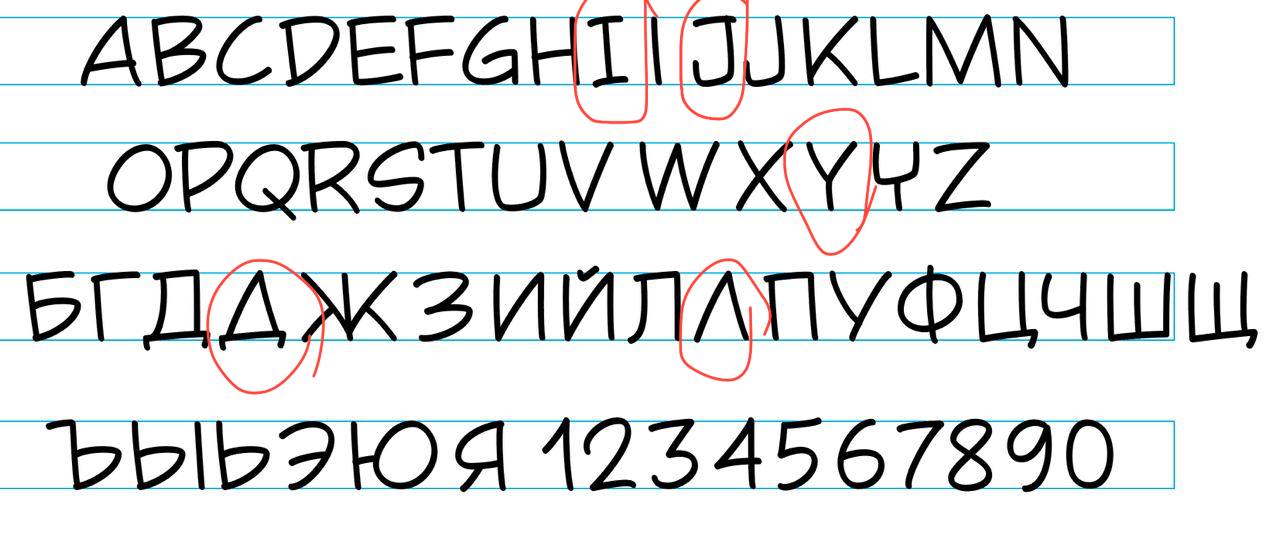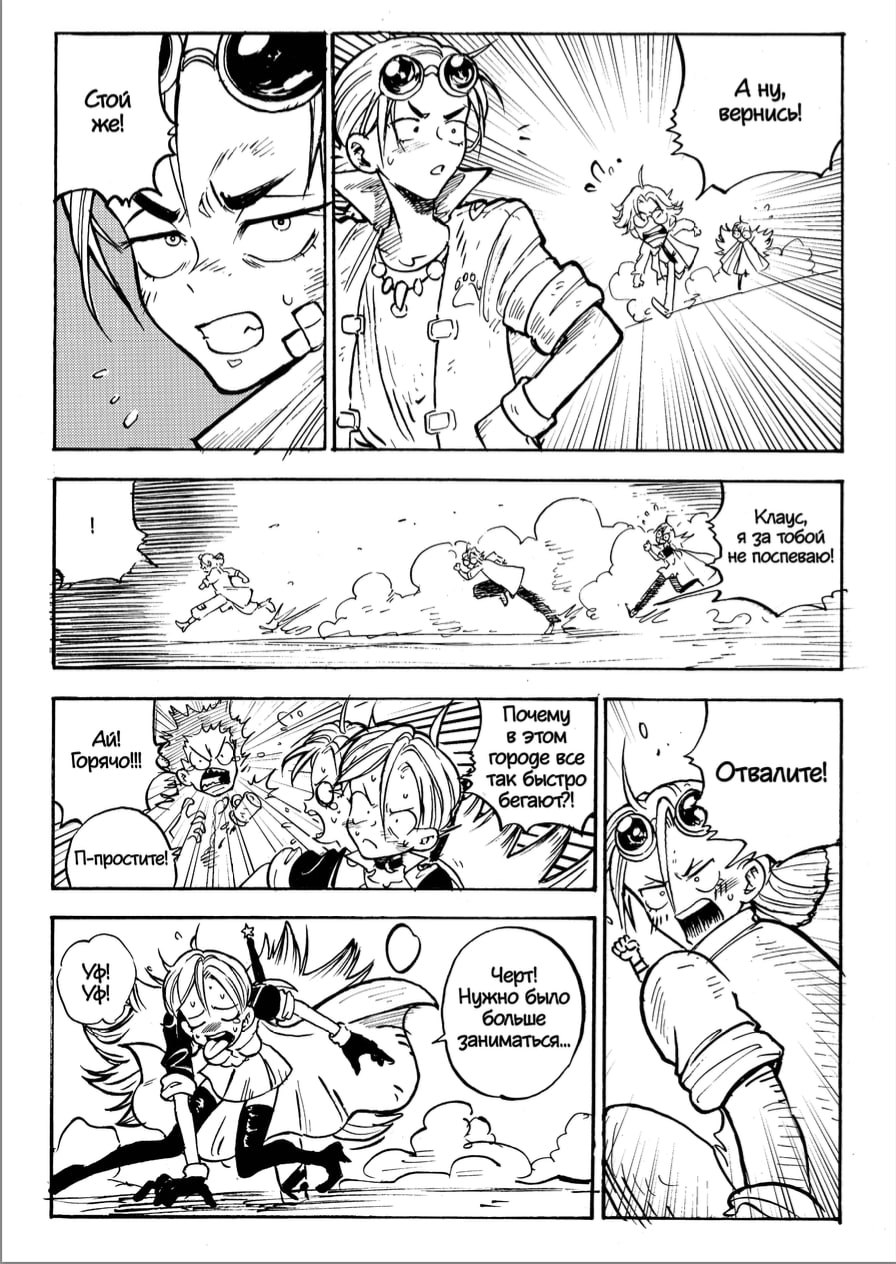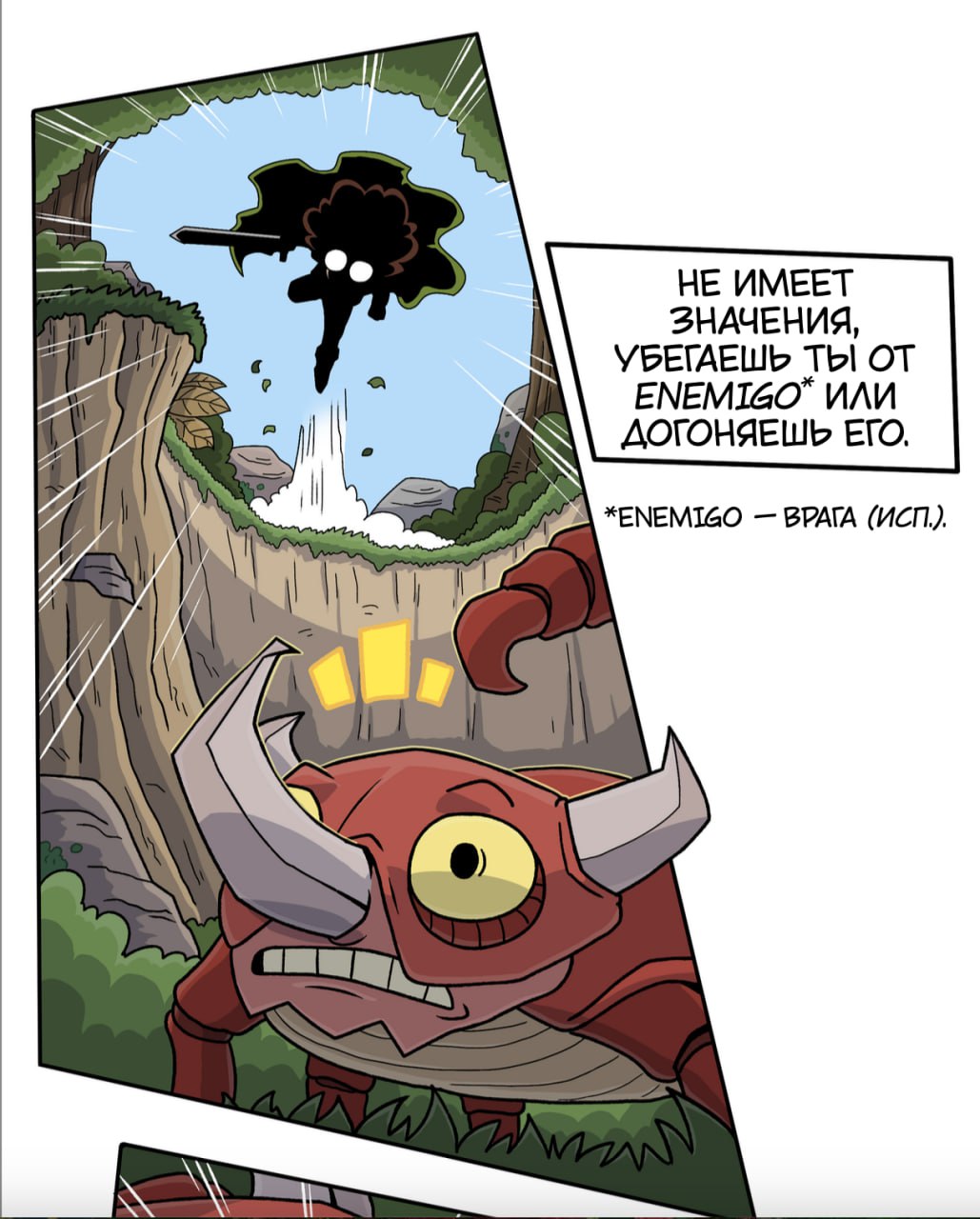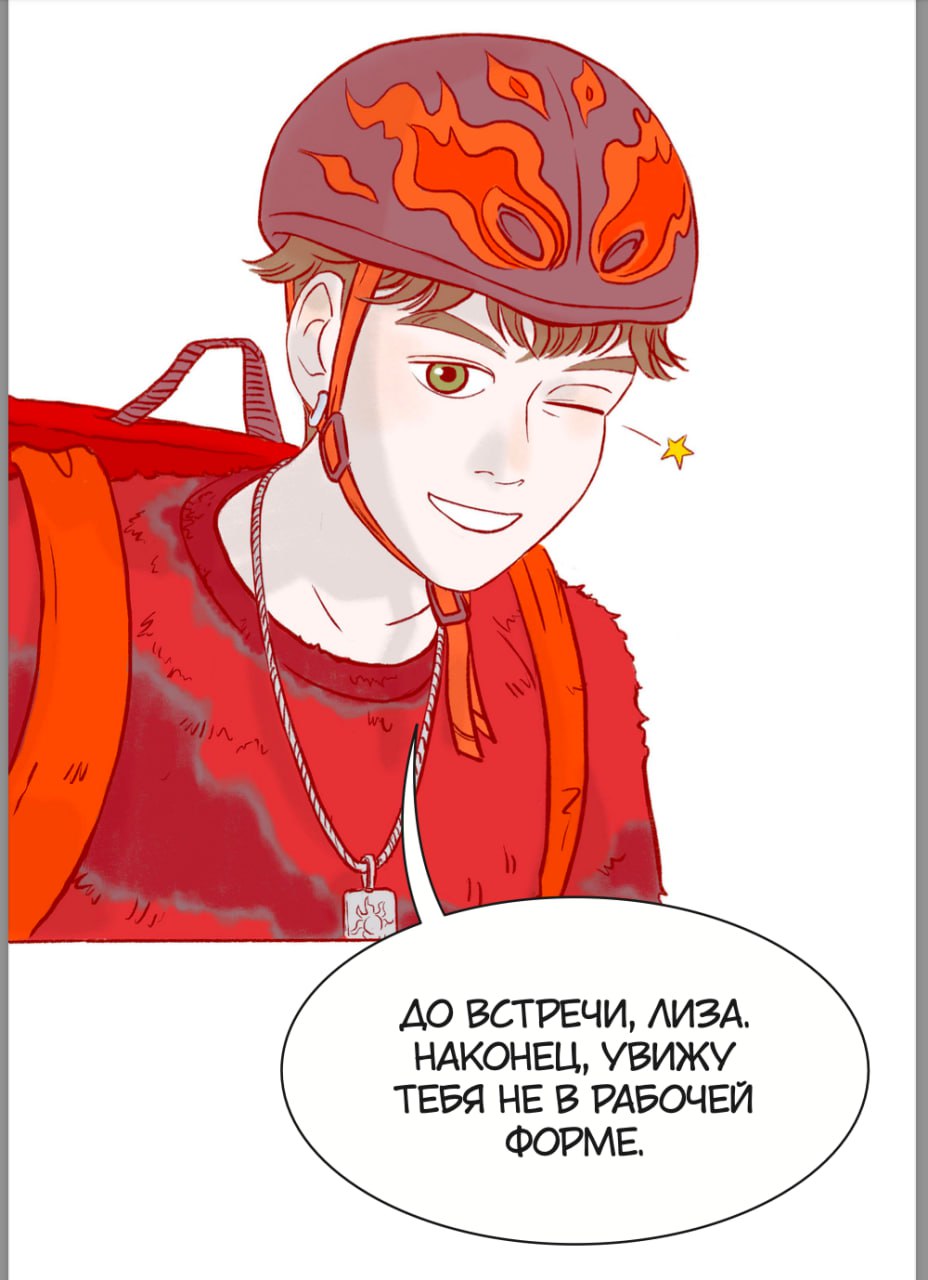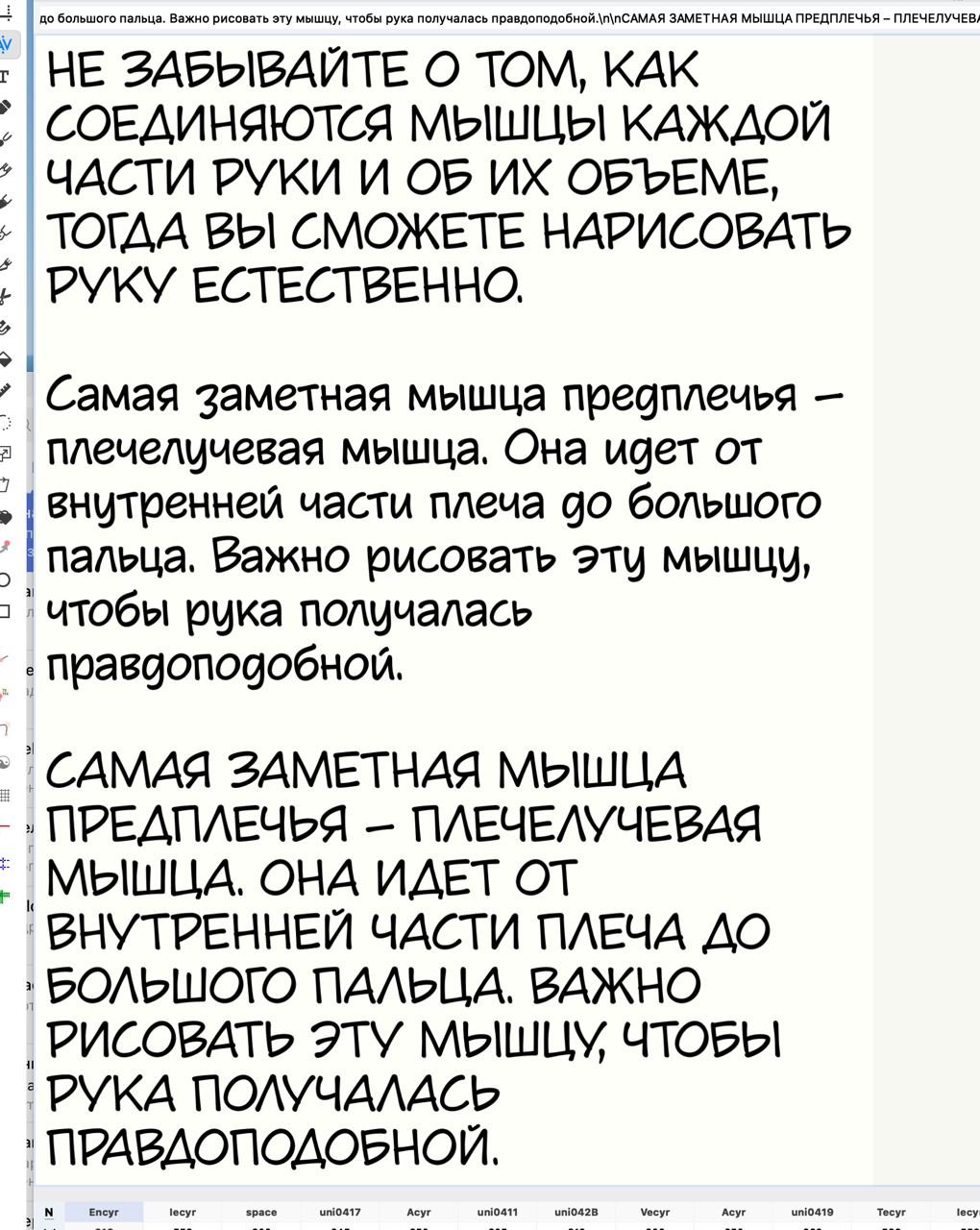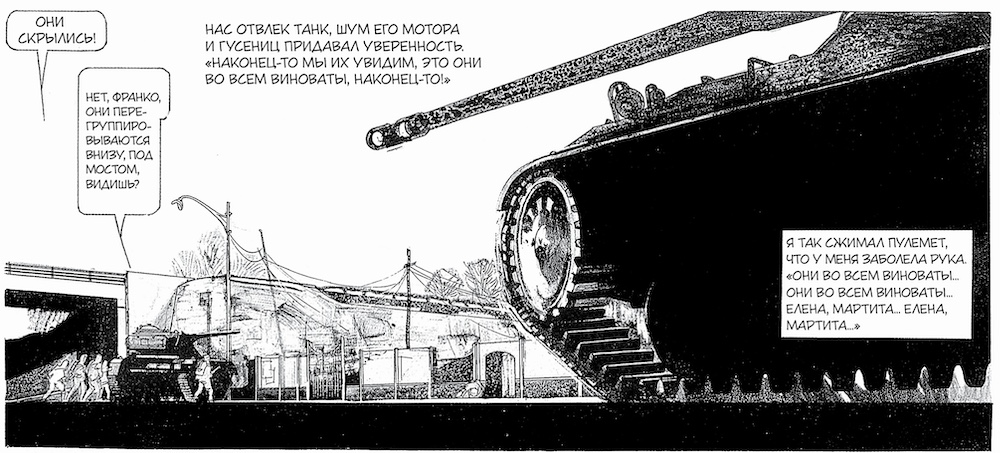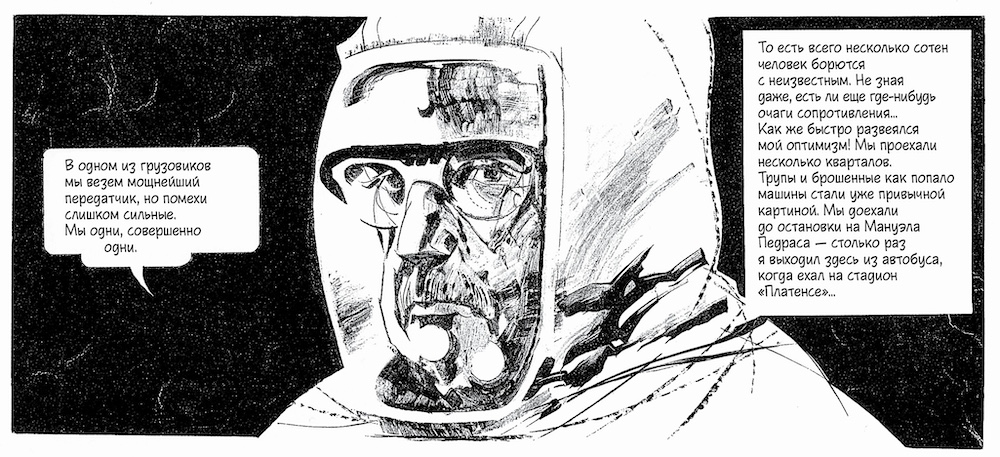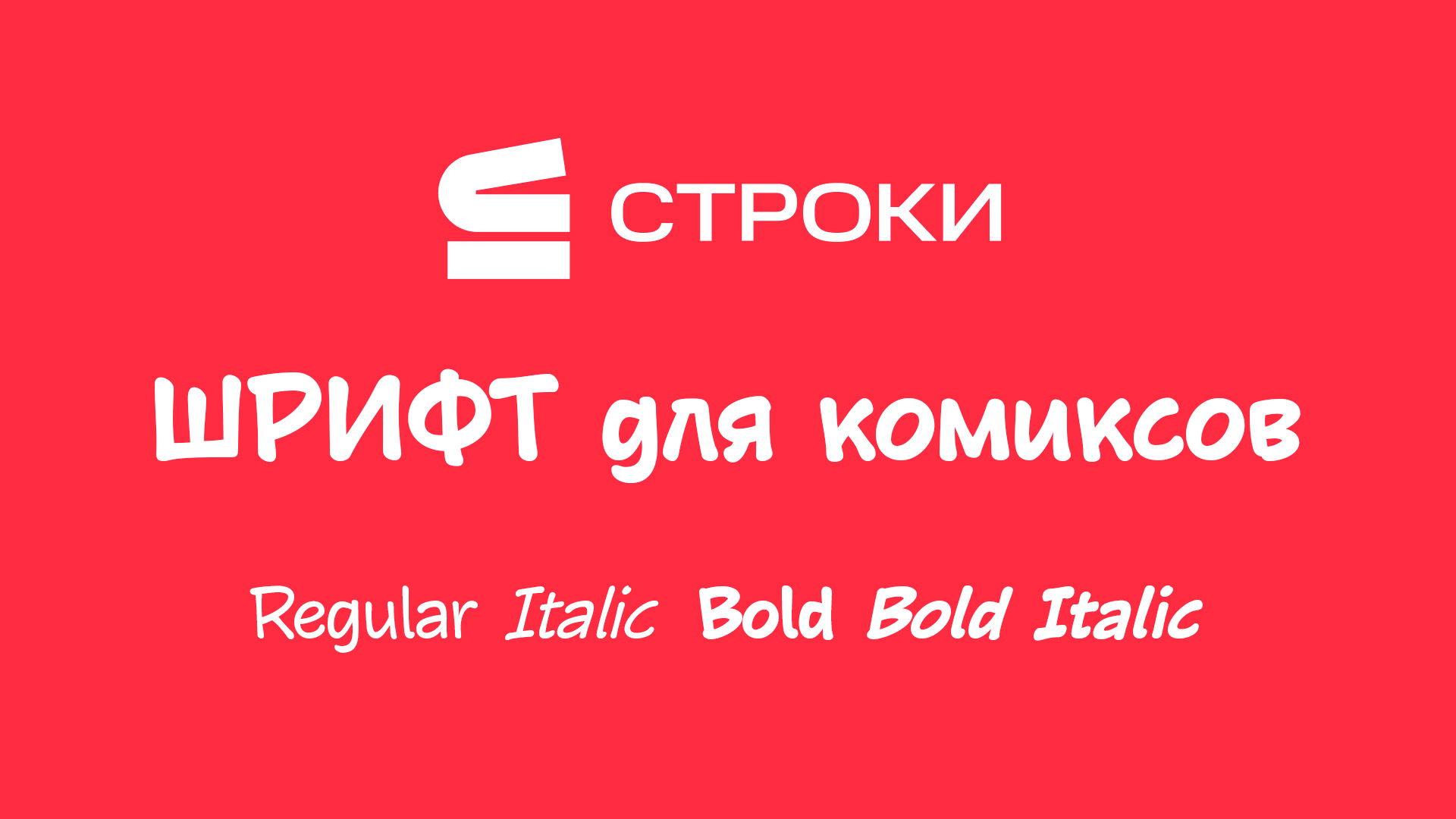
Шрифт для переводных и оригинальных комиксов, публикуемых на площадке и в приложении МТС Строки.
Четыре начертания. Прописные и строчные буквы.
Постепенно стараюсь рассказывать, что мы сделали к запуску раздела комиксов в “Строках”. И вот одно из моего любимого — собственный комиксный шрифт сервиса от лучшего специалиста в этом вопросе Захара Ящина!
Кажется, нет неподвластного ему леттеринга или каллиграфии! Вы видели его работы в русских адаптациях “Мауса”, “Персеполиса”, “Адель..” Тарди и многих, многих других.
Это было оперативно, профессионально и комфортно! Теперь у Строк есть шрифт имени сервиса, а мы не пользуем злосчастный все-мы-знаем-какой архив с адаптациями самых известных комиксных шрифтов от студий Blambot и ComicCraft, что все еще активно используется издателями. Делали четыре начертания для двух раскладок со строчными буквами в том числе. Тестим до сих пор, а Захар без сомнения лучший! 🥰